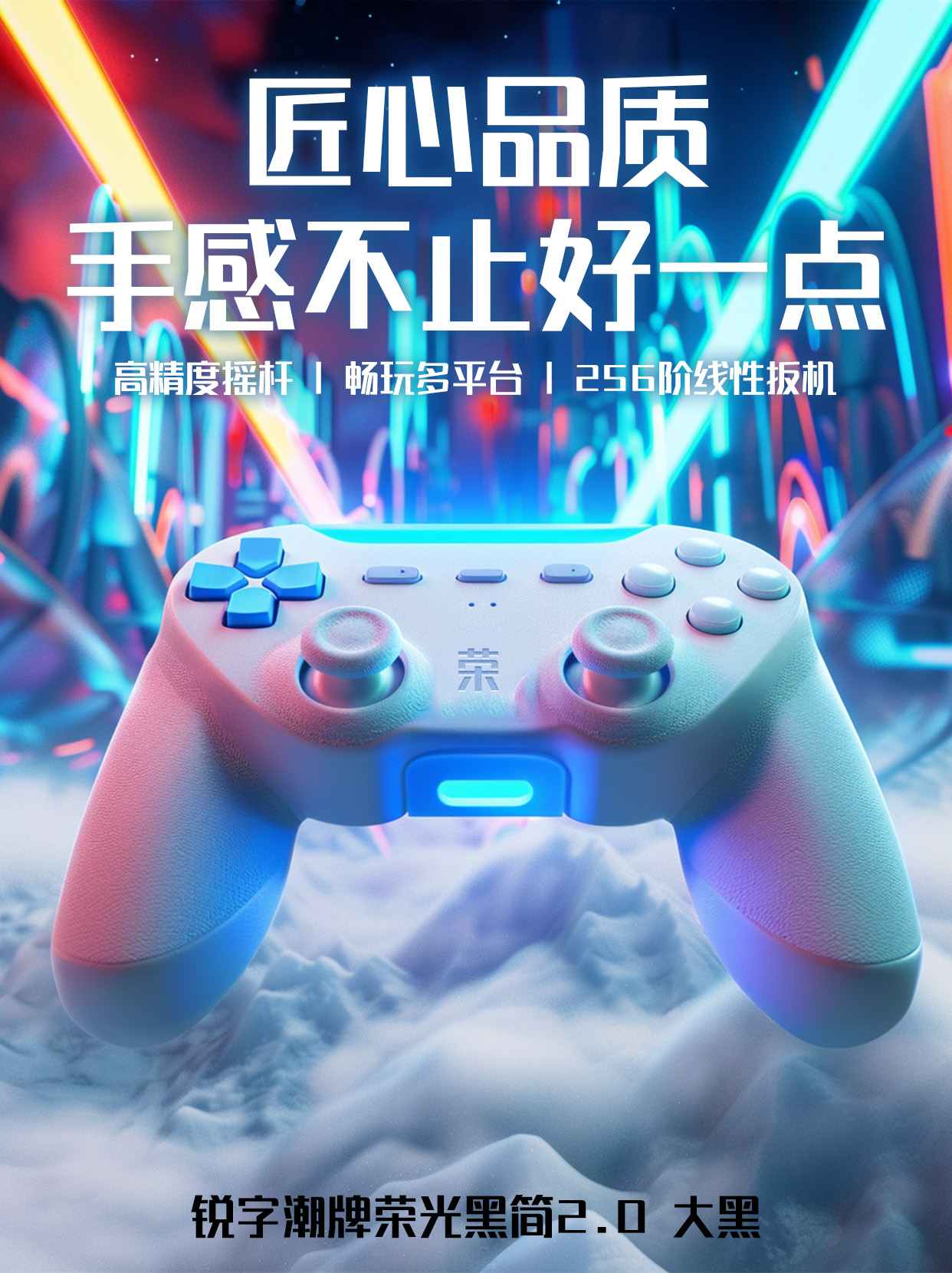
锐字潮牌荣光黑简2.0 大黑
REEJI-SunGB2.0 Bold
原锐字工房荣光黑简1.0 常规现已更新升级为锐字潮牌荣光黑简2.0 大黑
锐字潮牌荣光黑简2.0 大黑
简体
黑体
大黑(Bold)
锐字潮牌荣光黑是一款非常有力量感的标题字,笔画竖粗横细,笔风硬朗,变化得宜,具有醒目的视觉效果。非常适合于主标题设计、标语制作时使用。